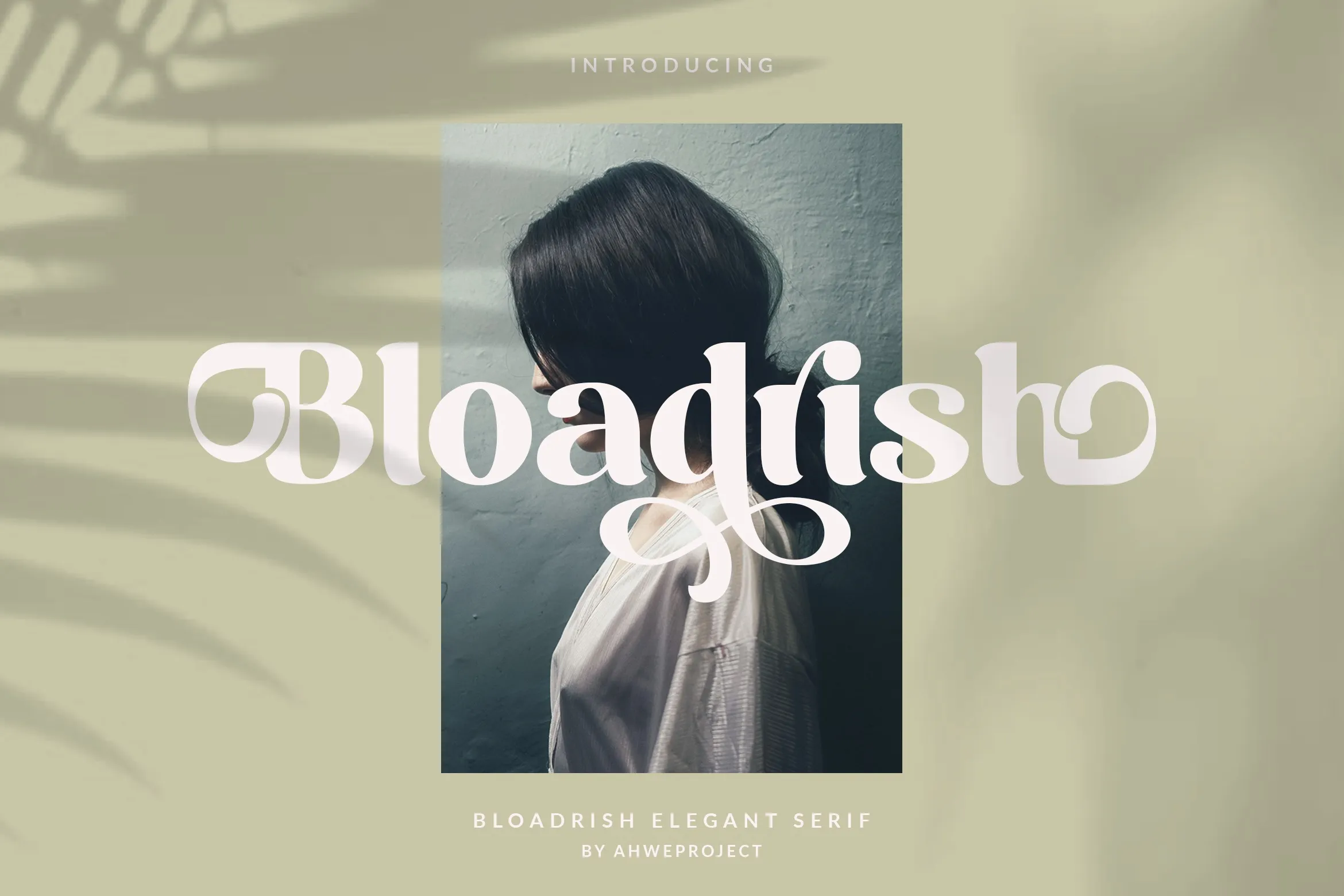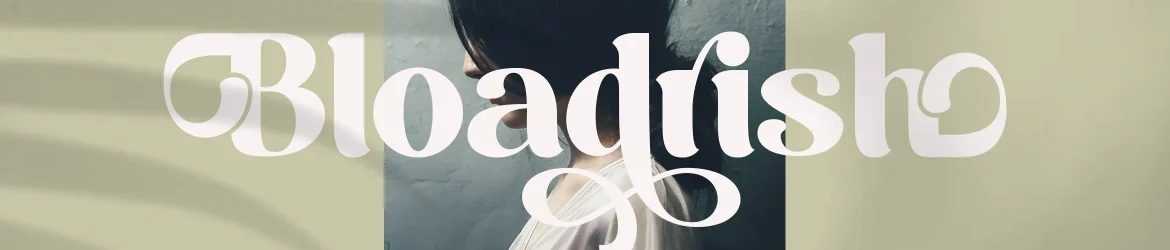
Bloadrish Font – Download Grátis
A Bloadrish Font é uma escolha perfeita para qualquer projeto que busque equilíbrio entre simplicidade moderna e sofisticação exuberante. Embora sua aparência possa sugerir um estilo futurista, ela transmite uma sensação de riqueza e elegância. Ideal tanto para trabalhos despojados quanto para projetos mais elaborados, a Bloadrish atende às necessidades dos designers que procuram trazer algum toque de beleza aos seus designs, seja em cartuns, jogos infantis, frases inspiradoras ou até mesmo ao nome de uma marca. Sua elegância permeia todas as suas aplicações, tornando-a uma excelente opção para qualquer projeto visual que exija um ar de sofisticação moderna.